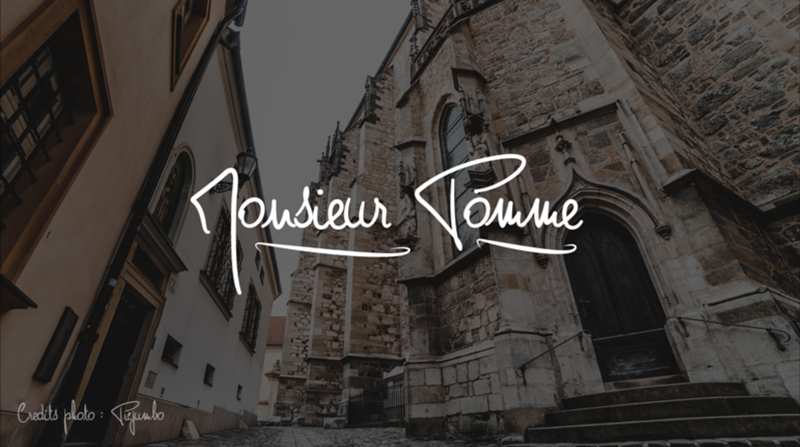
Monsieur Pomme Font – Download Grátis
A fonte Monsieur Pomme é uma delícia para os amantes do escritório artesanal. Desenvolvida pelo designer SVNprod, esta elegante fonte é perfeita para quem busca um toque delicado e sofisticado em seus projetos pessoais ou de uso íntimo. Com traços finos e linhas suaves, a Monsieur Pomme oferece uma experiência única na categoria de fontes de escritório artístico. Ideal para criar gráficos com estilo próprio, cartões personalizados ou até mesmo marcar presença em sua próxima reunião de trabalho, esta fonte é perfeita para quem valoriza a arte no cotidiano. Não espere mais para experimentar Monsieur Pomme na sua próxima criação! Visite o site svnprod.com para obter mais informações sobre essa e outras fontes excelentes.